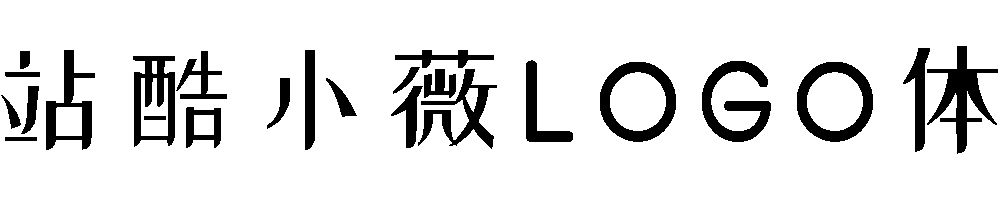
站酷小薇LOGO体是设计师李大卫送给女儿三周岁的礼物,由上海佐兹品牌设计工作室设计总监李大卫带领其工作室团队共成完成。设计师除了想把这款字体作为送给女儿的礼物,一个更大的愿望是希望这款字体可以填补免费字体中LOGO体的空缺。站酷小薇LOGO体采用GB2312汉字编码,共收录6763个汉字。
关于站酷字体:站酷公益字体,源自2014年的一次公益造字活动。由站酷ZCOOL的活跃字体设计师胡晓波及刘兵克发起这个项目,并设计最初的字形规范及基本部首,其余字形以众包的形式由分散在全国的79名设计师分别完成,最终一套好用并且免费的中文字体“站酷高端黑”诞生并在2014年圣诞发布。自从站酷高端黑之后,有更多的设计师团队和个人将字体赠送给站酷公益字体项目,交由站酷传播,给更多设计师使用。
站酷小薇LOGO体设计大胆创新,笔画与剑身相似,修长、谦和、灵秀,在简略了一些原字笔画的同时依然保持了很高的识别性高,是标志,标题的神器。